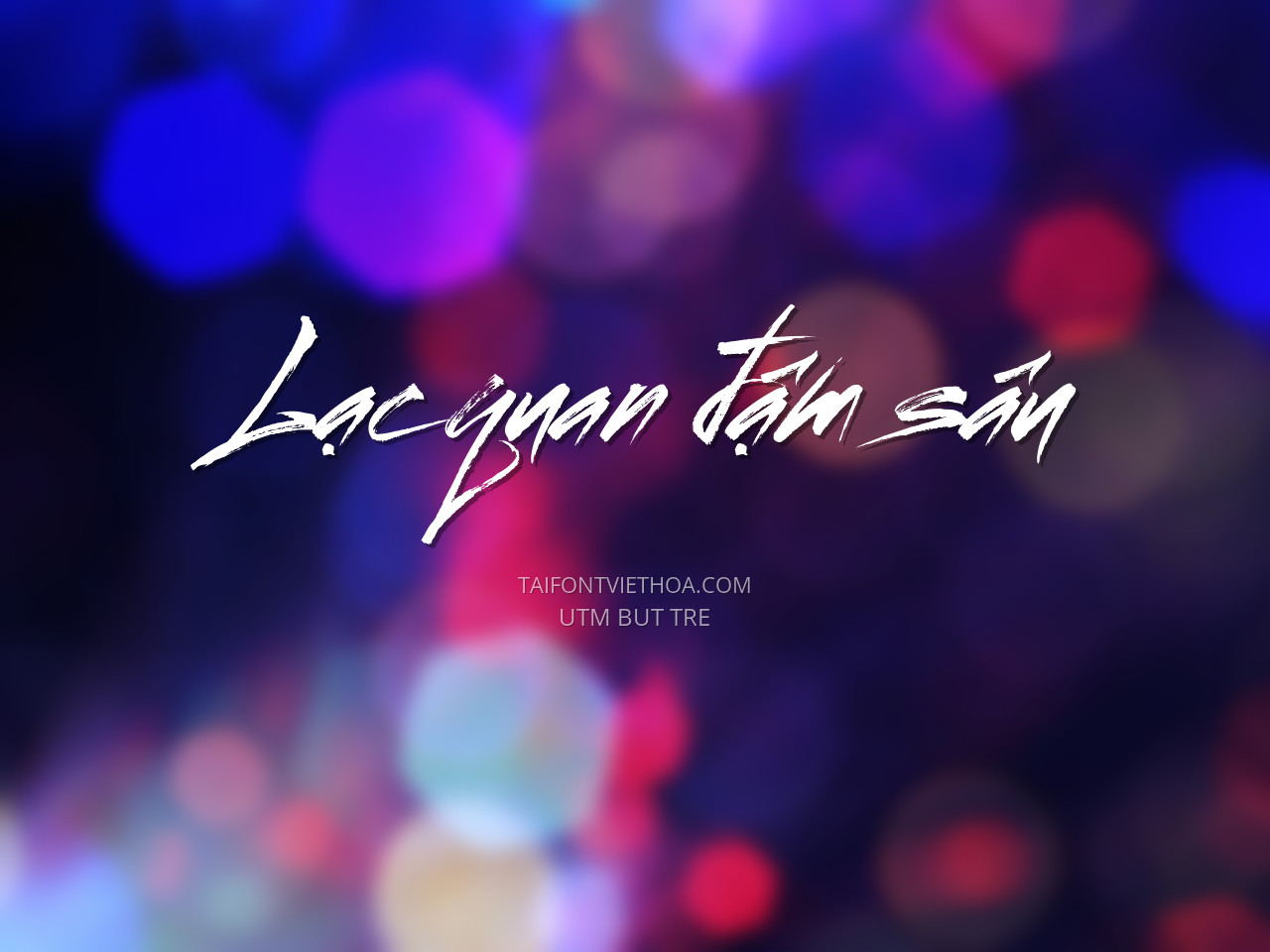
Font việt hóa UTM But Tre
Giới thiệu về font UTM But Tre
UTM But Tre là phiên bản Việt hóa của font But Tre – một kiểu chữ script mềm mại, duyên dáng và mang phong cách viết tay tự nhiên. Font gốc được thiết kế với các nét chữ uyển chuyển, thanh thoát và đầy cảm xúc, phù hợp cho các dự án thiết kế cá nhân hóa và nghệ thuật. Phiên bản Việt hóa đã được hoàn thiện để hỗ trợ đầy đủ tiếng Việt cùng hơn 100 ngôn ngữ khác, giúp mở rộng khả năng ứng dụng trong các dự án sáng tạo đa dạng.
Font UTM But Tre được taifontviethoa.com sưu tầm và chọn lọc kỹ càng nhằm phục vụ cộng đồng thiết kế Việt Nam. Phiên bản Việt hóa này giữ nguyên nét mềm mại, bay bổng của bản gốc, đồng thời tối ưu khả năng hiển thị tiếng Việt, rất phù hợp cho các dự án thiệp cưới, branding và thiết kế nghệ thuật.
Đặc điểm thiết kế và ứng dụng của UTM But Tre
UTM But Tre sở hữu cấu trúc script với các nét bút thanh mảnh, liên kết tự nhiên giữa các chữ cái và các ligature phong phú giúp tăng tính linh hoạt trong thiết kế. Font có độ tương phản nhẹ nhàng, tạo cảm giác mềm mại, lãng mạn và gần gũi, rất thích hợp cho các thiết kế mang phong cách cá nhân hóa và nghệ thuật cao.
Font phù hợp sử dụng trong thiệp cưới, thiệp mời, logo thương hiệu mỹ phẩm, poster nghệ thuật, bao bì sản phẩm thủ công và các dự án truyền thông mang tính cá nhân hóa cao. Các ngành nghề phù hợp gồm: tổ chức sự kiện, thời trang, làm đẹp, nghệ thuật sáng tạo, quảng cáo cá nhân hóa và thiết kế nội thất.